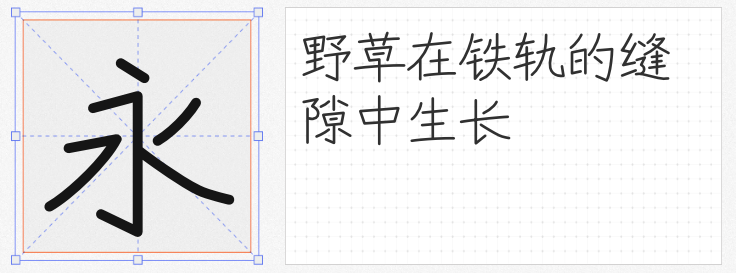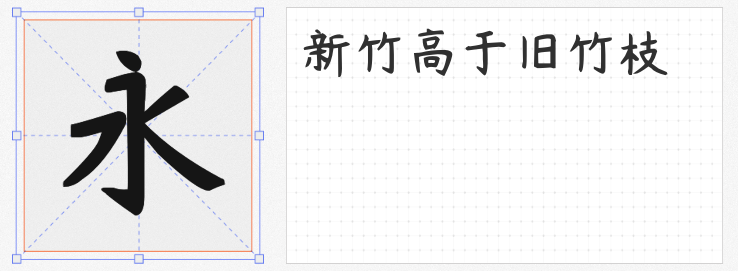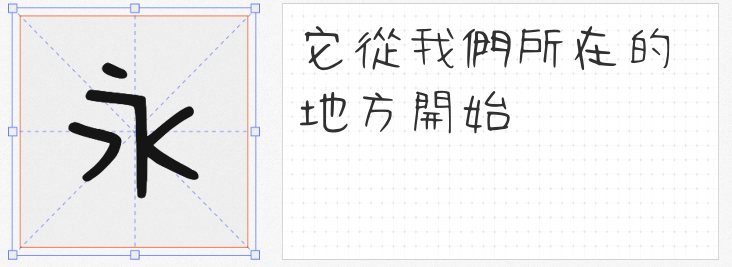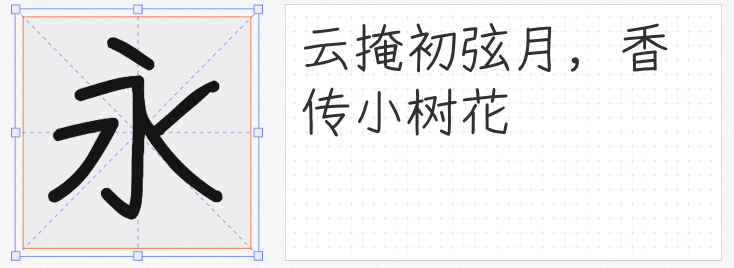
在Vlog封面设计或Plog图文排版中,一款契合主题的手写字体能瞬间提升作品的视觉感染力。今天推荐四款免费可商用的手写字体,它们风格各异却同样实用,助你轻松打造高级感设计。
1. 悠哉字体 常规
这款基于Y.OzFont二次创作的字体,通过笔划重组实现了全字符覆盖(含GB2312、通用规范汉字表及BIG5标准),6763个简体汉字与13058个繁体汉字满足多元场景需求。字体保留了手写特有的自然抖动感,笔画粗细过渡柔和,尤其适合美食、旅行类Vlog的标题设计,传递轻松惬意的氛围。
2. 写意体SC
如其名"Written"所暗示,这款字体完美复刻了中性笔书写的真实质感。笔画干净利落却暗藏书写力度变化,英文字母与中文搭配时呈现出和谐的视觉节奏。推荐用于科技类Vlog的图文排版,其克制的设计语言既能保持专业感,又通过手写元素打破冰冷感。
3. 清松手写体8
游清松先生打造的第八代作品延续了系列标志性的人性化设计,每个字都像独立创作的艺术品。笔画转折处保留了真实的书写停顿痕迹,特别适合母婴、生活类Plog的短文案排版。当需要营造"手写便签"效果时,这款字体能让数字内容瞬间充满生活气息。
4. 杨任东竹石体-Semibold
这款以竹石为灵感的字体,在保持手写自然感的同时融入了书法结构的张力。中宫收紧的笔画设计让小字号文本依然清晰可读,半粗体(Semibold)的重量感则适合作为标题使用。无论是古籍解读类Vlog的封面,还是国潮风格Plog的装饰元素,都能完美驾驭。